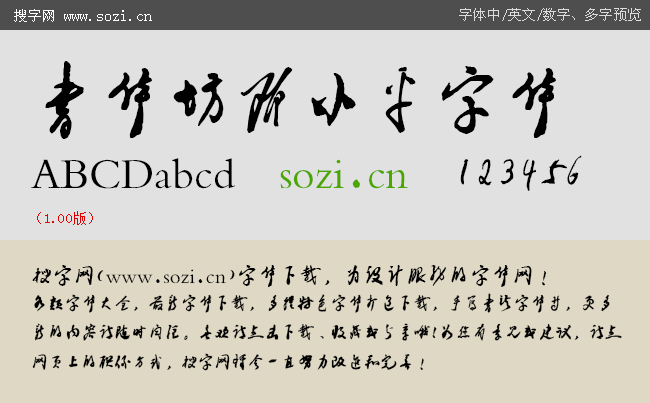
書體坊鄧小平行草字體
搜字網(wǎng)為大家提供一款書體坊鄧小平行草字體書法字體下載,此款字體是在鄧小平誕辰110周年之際,為紀(jì)念偉人,感恩小平,書體坊禚效鋒集字開發(fā)了鄧小平行草字庫。本套字庫,收漢字6770個(gè)?梢詰(yīng)用于平面廣告、名家題字、 藝術(shù)繪畫等領(lǐng)域,喜歡的用戶可下載收藏。